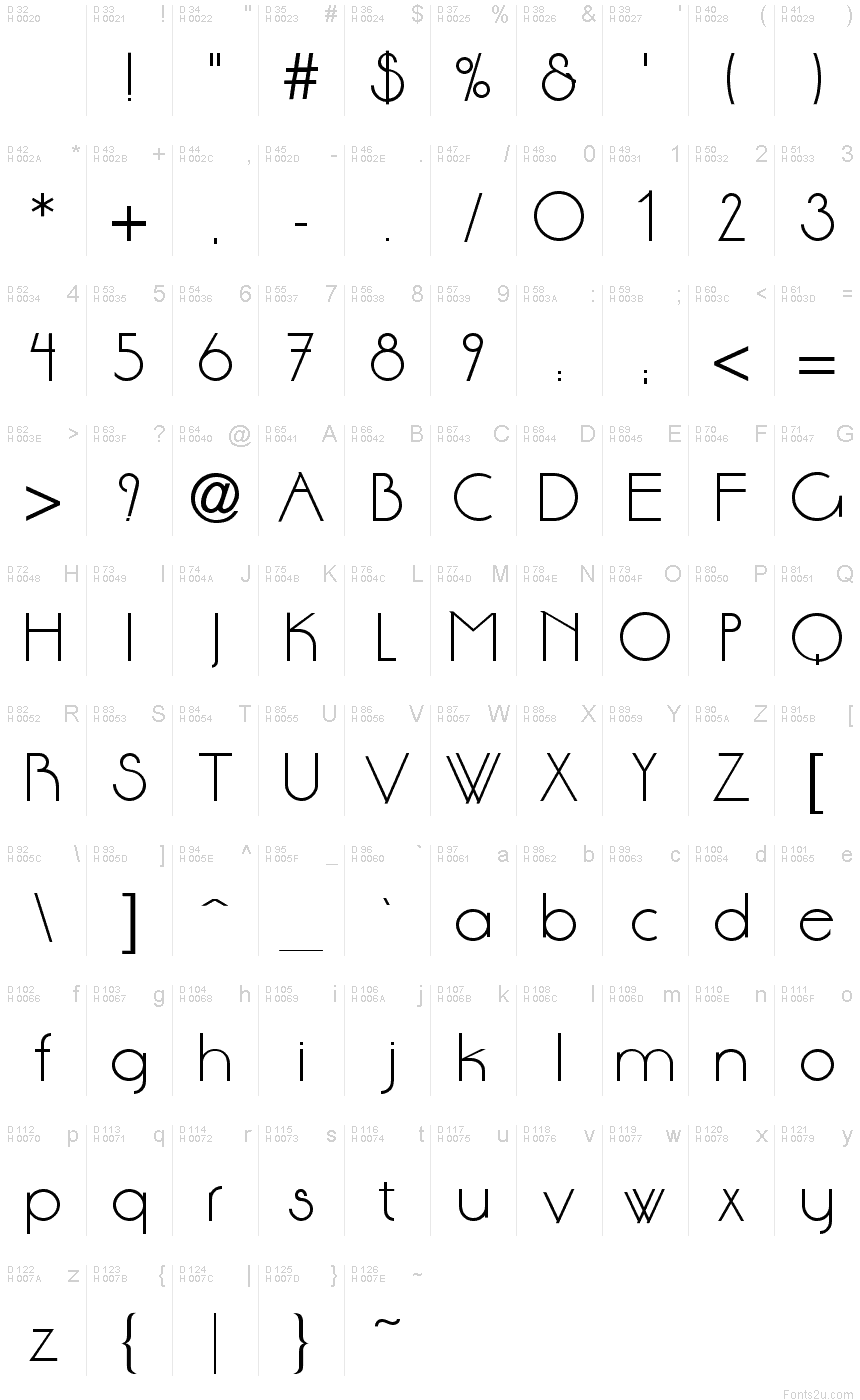
DS StandartCyr autorstwa Dubina Nikolay to darmowy, geometryczny, bezszeryfowy krój displayowy o przewiewnej, bardzo cienkiej konstrukcji. Okrągłe formy i zapętlone kreski sprawiają wrażenie rysowanych jedną, ciągłą linią, co nadaje tekstowi elegancki, niemal neonowy blask, pozbawiony jakiejkolwiek ostrości. Duże światła między literami oraz zaokrąglone łączenia zapewniają czytelność, zachowując jednocześnie eksperymentalny i futurystyczny charakter.
Dzięki DS StandartCyr nagłówki wydają się lekkie, ale pewne siebie, co czyni ten darmowy font świetnym wyborem do brandingu technologicznego, futurystycznych plakatów, minimalistycznych opakowań, modowych lookbooków, okładek albumów i interfejsów cyfrowych. Wygląda doskonale w większych rozmiarach, gdzie jej płynne krzywe mogą w pełni wybrzmieć. W tekście głównym warto połączyć ją z czytelnym krojem groteskowym lub humanistycznym o nieco większej grubości, aby nadać delikatnemu, „pływającemu” charakterowi DS StandartCyr odpowiednią wagę.